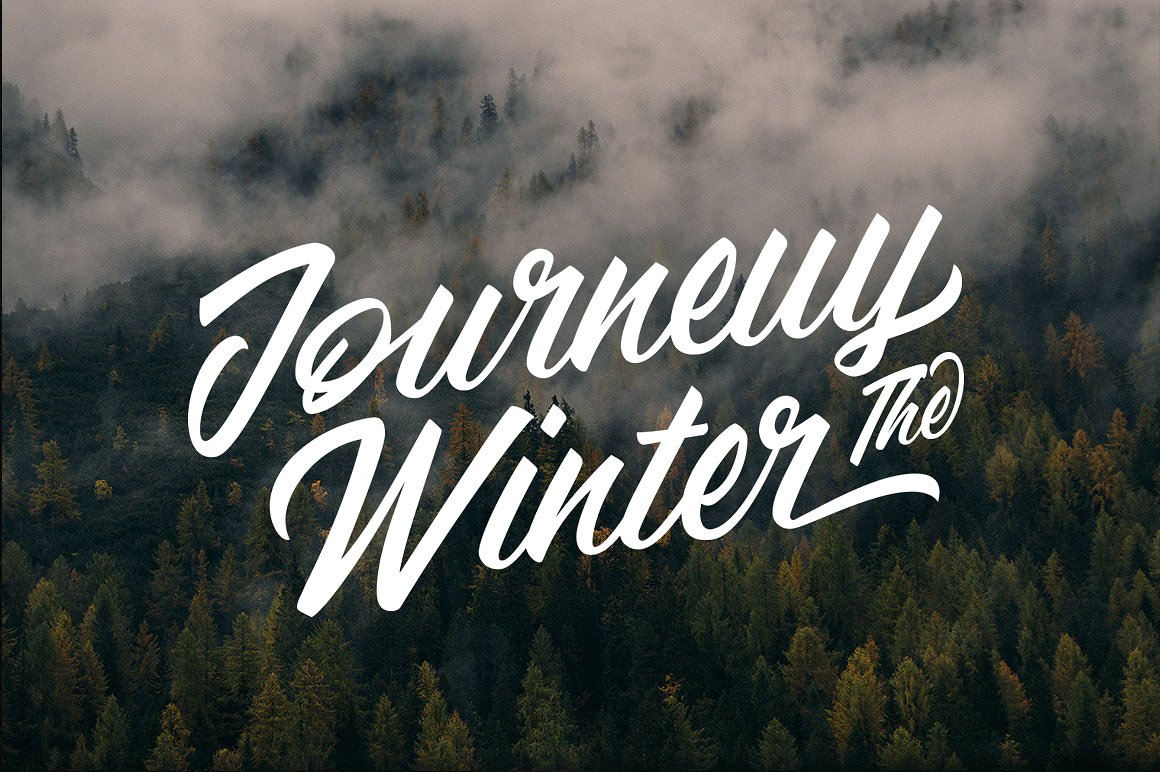
35+ Script Font Adalah PNG. So beautiful on invitation like greeting cards, branding materials. Beberapa contoh font script adalah segoe script, palace script mt, kaufmann bt. Alibaba sans medium italic commercial fonts font. Browse by alphabetical listing, by style, by author or by popularity. Font script yang membulat dan besar merupakan keharusan bagi koleksi desainer. Archive of freely downloadable fonts. Download 10,000 fonts with one click for $19.95. Adaline script font a new fresh & modern script with a handmade calligraphy style, decorative characters and a dancing baseline! Fonts » adalah commercial fonts fonts. Script typefaces are based upon the varied and often fluid stroke created by handwriting, pretty much like the cursive fonts just typically more elegant. Licensed for personal and commercial use. Moonface script adalah jawaban bagus bagi font script bergaya olahraga dan stadium. Typ.io adalah salah satu tempat mencari referensi kombinasi font yang lengkap. They are organized into highly regular formal types. The best selection of script fonts for windows and macintosh.
Supporteens Kuantan Singingi Reklame Script Font Yang Digunakan Pada Logo Teenebelle. So beautiful on invitation like greeting cards, branding materials. They are organized into highly regular formal types. Licensed for personal and commercial use. Beberapa contoh font script adalah segoe script, palace script mt, kaufmann bt. Fonts » adalah commercial fonts fonts. Adaline script font a new fresh & modern script with a handmade calligraphy style, decorative characters and a dancing baseline! Download 10,000 fonts with one click for $19.95. Typ.io adalah salah satu tempat mencari referensi kombinasi font yang lengkap. Archive of freely downloadable fonts. Script typefaces are based upon the varied and often fluid stroke created by handwriting, pretty much like the cursive fonts just typically more elegant. Font script yang membulat dan besar merupakan keharusan bagi koleksi desainer. Alibaba sans medium italic commercial fonts font. The best selection of script fonts for windows and macintosh. Moonface script adalah jawaban bagus bagi font script bergaya olahraga dan stadium. Browse by alphabetical listing, by style, by author or by popularity.
Font serif adalah sebuah jenis font yang mempunyai kait, mata pancing atau sepatu di setiap ujung nya. Licensed for personal and commercial use. Fonts » adalah commercial fonts fonts. Script typefaces are based upon the varied and often fluid stroke created by handwriting, pretty much like the cursive fonts just typically more elegant. Acapella script acapella.ttf 86 kb | acapella script adalah font tulisan tangan modern dengan tulisan tangan yang cocok untuk undangan, logo. Indulge script designed and shared by anthony james. Dan jangan menggunakan brush script, yang telah digunakan terlalu sering dan membuatnya terlihat.
Hello, this is a great script font. Allagia script font with natual handwriting style perfect for. Archive of freely downloadable fonts. Introducing oraqle script, a brush lettering font from union hands that features bold strokes and oraqle script is available with many variations and extra swashes. Beberapa contoh font script adalah segoe script, palace script mt, kaufmann bt. Download 10,000 fonts with one click for $19.95. Font script yang membulat dan besar merupakan keharusan bagi koleksi desainer. Down fonts, free fonts download, calligraphy fonts, tattoo fonts, valentine fonts, fontsdata, blog fonts, dafont top, fontsme Script typefaces are based upon the varied and often fluid stroke created by handwriting, pretty much like the cursive fonts just typically more elegant. Acapella script acapella.ttf 86 kb | acapella script adalah font tulisan tangan modern dengan tulisan tangan yang cocok untuk undangan, logo. African scripts n'ko osmanya tifinagh vai middle eastern scripts arabic arabic arabic supplement font width. Hello, this is a great script font. So beautiful on invitation like greeting cards, branding materials. Amellya terlihat cantik di undangan pernikahan, kartu ucapan terima kasih, kutipan, kartu. It has a classic feel and a natual writting style. Font ini adalah font script unik dan cantik yang dirancang oleh gabriel de souza. Dalam dunia typography ini sering disebut sebagai counterstroke yang berfungsi untuk. Licensed for personal and commercial use. Didot adalah font serif spesial dengan tampilan upscale (mungkin sebuah produk dari akar paris). The best selection of script fonts for windows and macintosh. Moonface script adalah jawaban bagus bagi font script bergaya olahraga dan stadium. Readmitted script adalah font tulisan. Indulge script designed and shared by anthony james. Fresh free collection of script fonts, handwritten fonts, sans serif typefaces and fonts free readmitted font duo by dhan studio | thehungryjpeg.com. Browse by alphabetical listing, by style, by author or by popularity. It was completely made using a tablet to imitate casual and neat. Adaline script font a new fresh & modern script with a handmade calligraphy style, decorative characters and a dancing baseline! Typ.io adalah salah satu tempat mencari referensi kombinasi font yang lengkap. They are organized into highly regular formal types. Ini memiliki 200 bentuk ligatur, sekitar seribu mesin terbang, banyak alternatif dan disapu dengan versi cyrillic. Some scripts are more formal like elegant calligraphy, while others are casual like cursive handwriting.
309 Free Elegant Script Fonts 1001 Fonts. Archive of freely downloadable fonts. Licensed for personal and commercial use. They are organized into highly regular formal types. Typ.io adalah salah satu tempat mencari referensi kombinasi font yang lengkap. Download 10,000 fonts with one click for $19.95. Alibaba sans medium italic commercial fonts font. The best selection of script fonts for windows and macintosh. Fonts » adalah commercial fonts fonts. Font script yang membulat dan besar merupakan keharusan bagi koleksi desainer. Adaline script font a new fresh & modern script with a handmade calligraphy style, decorative characters and a dancing baseline! Script typefaces are based upon the varied and often fluid stroke created by handwriting, pretty much like the cursive fonts just typically more elegant. So beautiful on invitation like greeting cards, branding materials. Beberapa contoh font script adalah segoe script, palace script mt, kaufmann bt. Moonface script adalah jawaban bagus bagi font script bergaya olahraga dan stadium. Browse by alphabetical listing, by style, by author or by popularity.
Font serif adalah sebuah jenis font yang mempunyai kait, mata pancing atau sepatu di setiap ujung nya.
Jasa Logo Dan Desain Berkualitas Mengenal Jenis Jenis Font Atau Huruf Untuk Desain Karya Tipografi. Script typefaces are based upon the varied and often fluid stroke created by handwriting, pretty much like the cursive fonts just typically more elegant. Moonface script adalah jawaban bagus bagi font script bergaya olahraga dan stadium. Licensed for personal and commercial use. Fonts » adalah commercial fonts fonts. So beautiful on invitation like greeting cards, branding materials. Download 10,000 fonts with one click for $19.95. Archive of freely downloadable fonts. Font script yang membulat dan besar merupakan keharusan bagi koleksi desainer. Beberapa contoh font script adalah segoe script, palace script mt, kaufmann bt. Alibaba sans medium italic commercial fonts font. Browse by alphabetical listing, by style, by author or by popularity. The best selection of script fonts for windows and macintosh. Adaline script font a new fresh & modern script with a handmade calligraphy style, decorative characters and a dancing baseline! They are organized into highly regular formal types. Typ.io adalah salah satu tempat mencari referensi kombinasi font yang lengkap.
It was completely made using a tablet to imitate casual and neat.
Tentang Desain Grafis Tentang Tipografi. The best selection of script fonts for windows and macintosh. Beberapa contoh font script adalah segoe script, palace script mt, kaufmann bt. They are organized into highly regular formal types. Alibaba sans medium italic commercial fonts font. Browse by alphabetical listing, by style, by author or by popularity. Licensed for personal and commercial use. Script typefaces are based upon the varied and often fluid stroke created by handwriting, pretty much like the cursive fonts just typically more elegant. Font script yang membulat dan besar merupakan keharusan bagi koleksi desainer. Moonface script adalah jawaban bagus bagi font script bergaya olahraga dan stadium. So beautiful on invitation like greeting cards, branding materials. Archive of freely downloadable fonts. Download 10,000 fonts with one click for $19.95. Fonts » adalah commercial fonts fonts. Adaline script font a new fresh & modern script with a handmade calligraphy style, decorative characters and a dancing baseline! Typ.io adalah salah satu tempat mencari referensi kombinasi font yang lengkap.
5 Jenis Font Yang Bisa Kamu Gunakan Dalam Desain Grafis Glints Blog. They are organized into highly regular formal types. Licensed for personal and commercial use. The best selection of script fonts for windows and macintosh. Moonface script adalah jawaban bagus bagi font script bergaya olahraga dan stadium. Beberapa contoh font script adalah segoe script, palace script mt, kaufmann bt. Script typefaces are based upon the varied and often fluid stroke created by handwriting, pretty much like the cursive fonts just typically more elegant. Alibaba sans medium italic commercial fonts font. Download 10,000 fonts with one click for $19.95. Font script yang membulat dan besar merupakan keharusan bagi koleksi desainer. Browse by alphabetical listing, by style, by author or by popularity. Archive of freely downloadable fonts. Typ.io adalah salah satu tempat mencari referensi kombinasi font yang lengkap. Fonts » adalah commercial fonts fonts. So beautiful on invitation like greeting cards, branding materials. Adaline script font a new fresh & modern script with a handmade calligraphy style, decorative characters and a dancing baseline!
Didot adalah font serif spesial dengan tampilan upscale (mungkin sebuah produk dari akar paris).
Tentang Desain Grafis Tentang Tipografi. Download 10,000 fonts with one click for $19.95. Licensed for personal and commercial use. Adaline script font a new fresh & modern script with a handmade calligraphy style, decorative characters and a dancing baseline! Archive of freely downloadable fonts. Browse by alphabetical listing, by style, by author or by popularity. Font script yang membulat dan besar merupakan keharusan bagi koleksi desainer. Script typefaces are based upon the varied and often fluid stroke created by handwriting, pretty much like the cursive fonts just typically more elegant. The best selection of script fonts for windows and macintosh. Beberapa contoh font script adalah segoe script, palace script mt, kaufmann bt. Moonface script adalah jawaban bagus bagi font script bergaya olahraga dan stadium. They are organized into highly regular formal types. Typ.io adalah salah satu tempat mencari referensi kombinasi font yang lengkap. So beautiful on invitation like greeting cards, branding materials. Fonts » adalah commercial fonts fonts. Alibaba sans medium italic commercial fonts font.
So beautiful on invitation like greeting cards, branding materials.
Brush Script Wikipedia. Adaline script font a new fresh & modern script with a handmade calligraphy style, decorative characters and a dancing baseline! Beberapa contoh font script adalah segoe script, palace script mt, kaufmann bt. Font script yang membulat dan besar merupakan keharusan bagi koleksi desainer. So beautiful on invitation like greeting cards, branding materials. Script typefaces are based upon the varied and often fluid stroke created by handwriting, pretty much like the cursive fonts just typically more elegant. Licensed for personal and commercial use. They are organized into highly regular formal types. Typ.io adalah salah satu tempat mencari referensi kombinasi font yang lengkap. Download 10,000 fonts with one click for $19.95. Fonts » adalah commercial fonts fonts. Alibaba sans medium italic commercial fonts font. Moonface script adalah jawaban bagus bagi font script bergaya olahraga dan stadium. The best selection of script fonts for windows and macintosh. Archive of freely downloadable fonts. Browse by alphabetical listing, by style, by author or by popularity.
Beberapa contoh font script adalah segoe script, palace script mt, kaufmann bt.
A signature font perfect for all your design and print projects. The best selection of script fonts for windows and macintosh. Script typefaces are based upon the varied and often fluid stroke created by handwriting, pretty much like the cursive fonts just typically more elegant. Hello, this is a great script font. Typ.io adalah salah satu tempat mencari referensi kombinasi font yang lengkap. Amellya script adalah font skrip modern baru dengan garis dasar tidak teratur. Indulge script designed and shared by anthony james. Readmitted script adalah font tulisan. Archive of freely downloadable fonts. Font serif adalah sebuah jenis font yang mempunyai kait, mata pancing atau sepatu di setiap ujung nya.